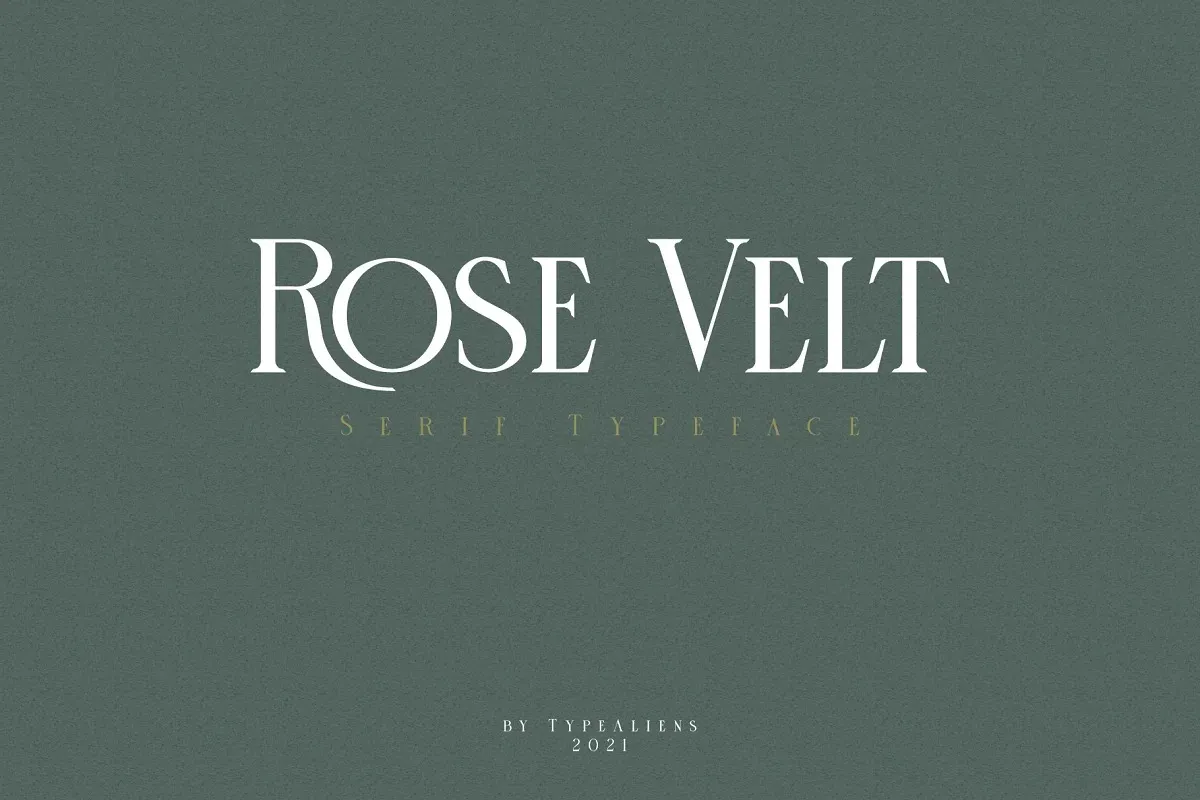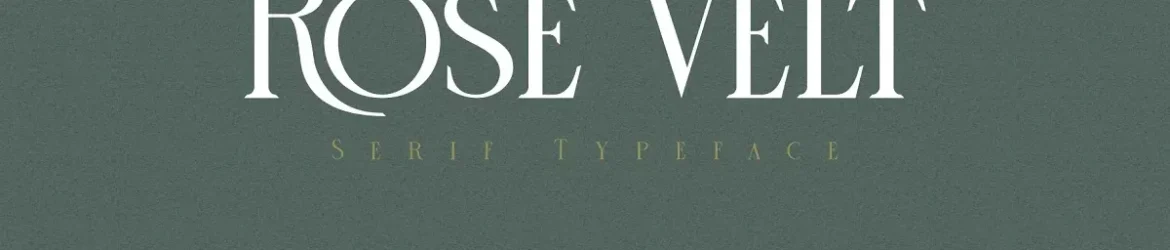
A Rose Velt é uma fonte serif vintage e sofisticada, desenvolvida pelo site 99designs. Suas linhas finas e elegantes criam um equilíbrio perfeito entre classe clássica e modernidade vibrante. Com letras maiúsculas e minúsculas que têm formas semelhantes, a Rose Velt é uma escolha perfeita para designers que buscam um toque de sofisticação em suas criações gráficas. Esta fonte é muito versátil e fácil de aplicar em variedades de projetos, como logotipos, capas de revistas limpas e elegantes, cartazes e flyers de propaganda moderna. O que torna a Rose Velt uma opção irresistível para qualquer designer gráfico.